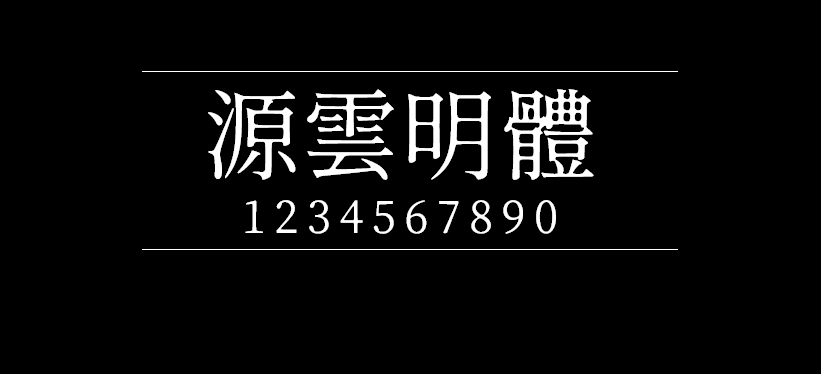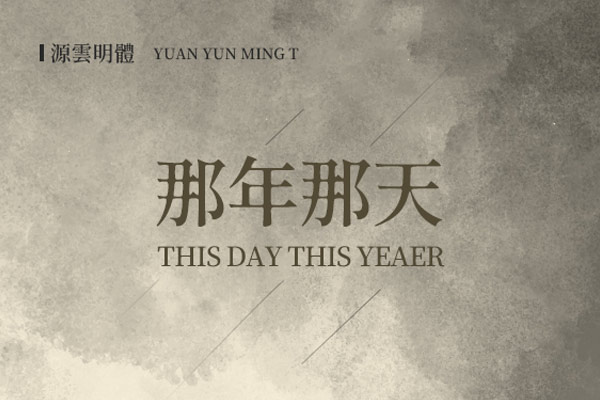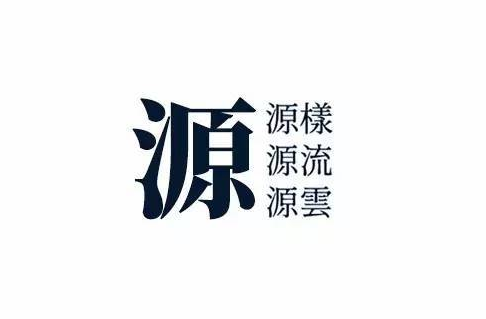
字体下载 源云明体
源云明体
推荐过不少修改自思源黑体、思源宋体的开源免费字体,这两款由Google和Adobe合作共同开发的字体已经为无数设计师及开发者解决字体问题,并奠定新的字体发展典范,最大价值可能不一定是价格上免费,而是开放源代码特性使它可以再次被用于创作出新字体,例如:思源真黑体、思源柔黑体或修改自思源宋体的装甲明朝、源界明朝等等,不过有点可惜的是这些字体都出自于日本设计师,一直到写这篇文章前好像都还没有国人创作的字体风格。
源云明体